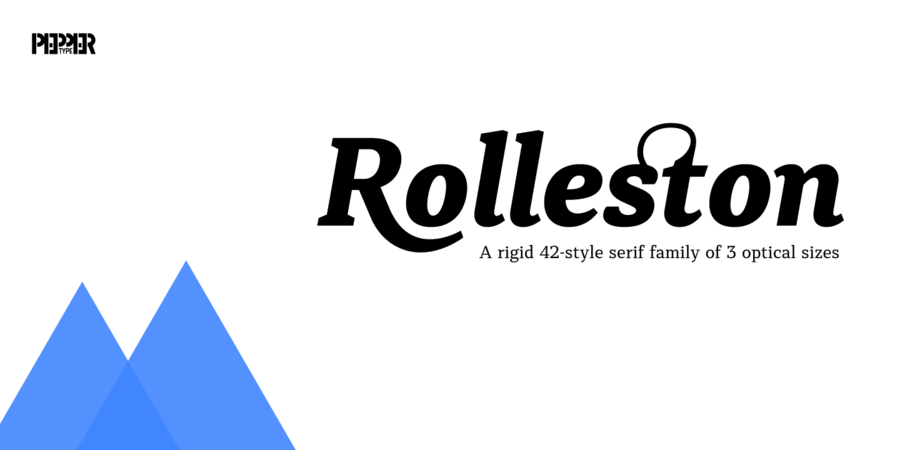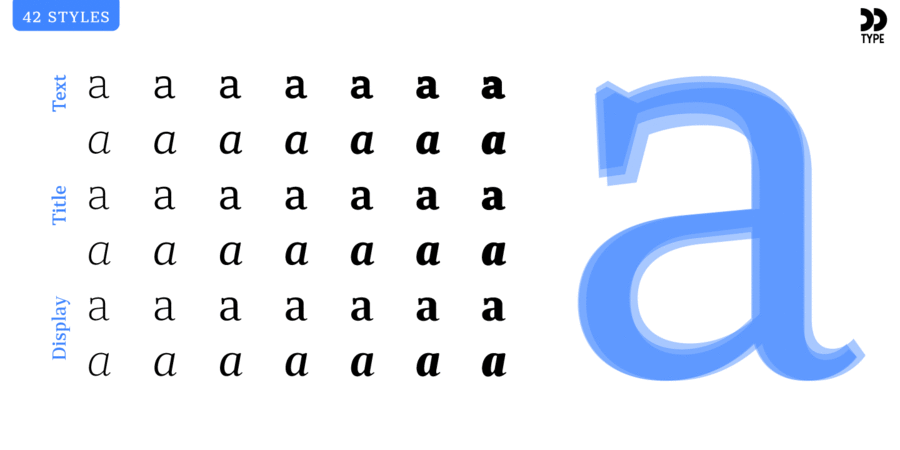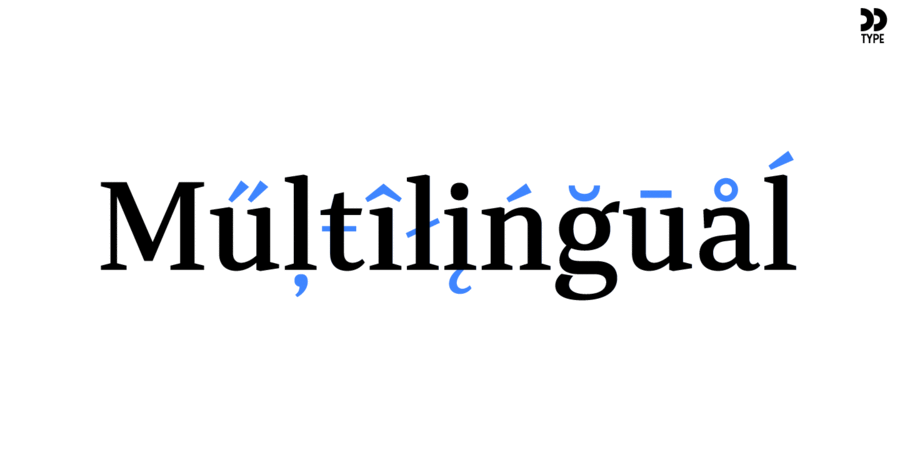
Rolleston Text – частина шрифтового сімейства Rolleston. Його 14 накреслень створені спеціально для тексту в книгах, журналах чи на сайтах.
Rolleston – статичне шрифтове сімейство з клиноподібними зарубками. Гарнітура містить 42 накреслення, по 14 для трьох оптичних розмірів: Text, Title, та Display.
Ця гарнітура підтримує десятки мов на латиниці та кирилиці, містить різні опентайп-фічи, безліч лігатур і великий набір альтернативних гліфів. Це дозволяє створювати унікальні заголовки та красиві збалансовані тексти.
Шрифт розробив Олег Ліщук у 2018 році.
Асоціації з сімейством шрифтів Rolleston TextОсобистість і характер гарнітури:
тонкий, легкий, делікатний, спокійний, рівний, гармонійний, врівноважений, космополітичний, технічний, сучасний, точний, логічний, статичний, культурний, освічений, серйозний, розумний, твердий, чіткий, різкий, худий, ввічливий, динамічний, універсальний, зрозумілий, діловий, помірний, практичний, оптимальний, доступний, стійкий, формальний, якісний, міський, акуратний, стабільний, солідний, переконливий, мотивуючий, відповідальний, сильний, міцний, мужній, важливий, авторитетний, значний, суворий, потужний, важкий, щільний, помітний, яскравий, активний
— Гарнітура асоціюється з віком: